FONT x FAN HYBRID 5
フォント・アライアンス・ネットワークは、国内外全93ブランドによる日本語フォントを中心に豊富なカテゴリ&スタイルのフォントを収録した国内最大規模となる12,817フォントを収録したフォントパッケージ製品「FONT x FAN HYBRID 5」が2018年11月16日から発売を開始した。
「FONT x FAN HYBRID 5」には多用しやすいベーシックフォントやUD書体をはじめ高額のプロ用フォントを中心に国内最大級の日本語総合フォント841フォントを収録。
その他様々な用途に使用できるよう多数のカテゴリ&スタイルのフォントを収録し、パッケージ全体でも国内最多規模となる12,817フォントを収録したハイブリッド仕様の超ハイコストパフォーマンスなフォントパックを実現し、初心者からプロユーザーまで使える、フォントの魅力を凝縮した日本語を中心とした総合フォントパック集になっている。
「FONT x FAN HYBRID 5」追加新書体活用例
「FONT x FAN HYBRID 5」書体活用例
また初回特典として、昭和書体『昭和書体セレクトパック2(ダウンロード版、定価7,000円)』のTrueTypeまたはOpenTypeが付属される。
「昭和書体」活用例
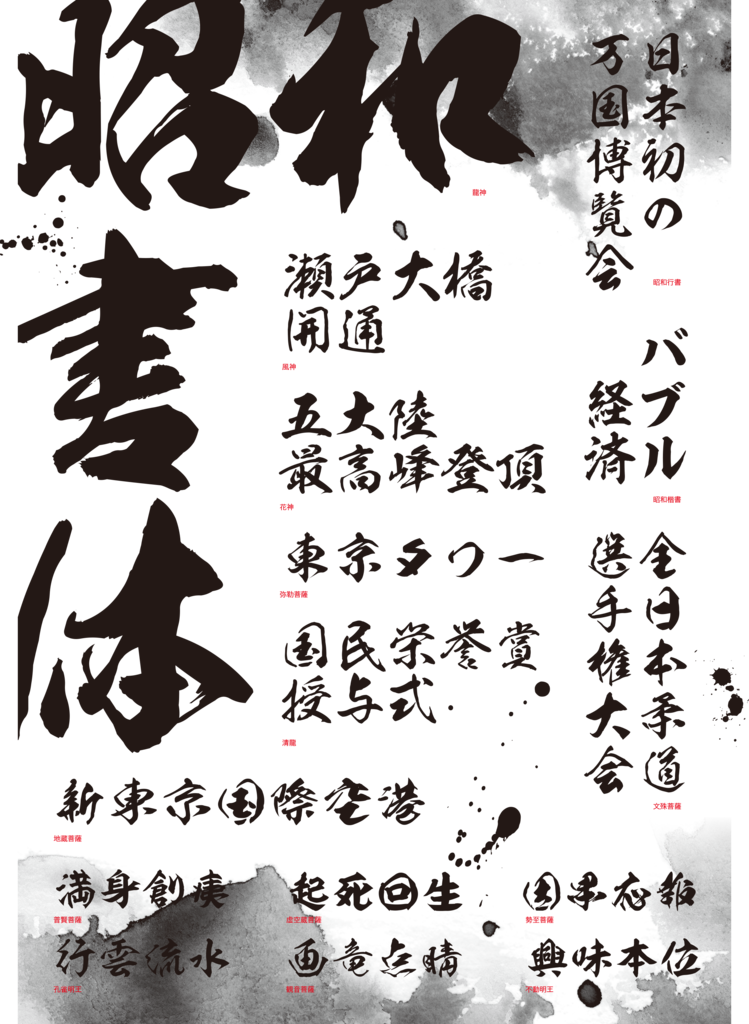
FONT x FAN HYBRID 5(フォントファン ハイブリッド 5)特長
1.コスパ度国内最大の総合フォントパック集
個別のフォント製品や日本語総合フォント製品を多数収録。
2.国内最多規模のフォントパック
国内最大級となる12817のフォントを収録、年間ライセンス製品ものはもちろん売り切り型のフォント製品の中でも最大規模の収録となる。
3.FONT x FAN HYBRIDシリーズ第5弾!今回も増量&大幅パワーアップ
新作、未公開フォントなど日本語フォント34フォント、欧文フォント228フォントなど多数追加収録
5.初回特典として迫力ある筆文字として人気の昭和書体『昭和書体セレクトパック2(ダウンロード版、定価7,000円)』を特別収録。
多用し易いベーシックフォントから人気の筆文字系、デザイン系まで広く収録。プロ用をはじめ人気のUD書体、デザイン筆文字その他新作フォントを追加収録。
クリエイターズ手書き風仮名フォント『ガールズフォント』/ OpenType
レトロ風,シネマ風等収録した『レトロ仮名フォント』/ OpenType
タイトルに最適なカナフォント集『カナフェイス44』/ TrueType
ちらしやPOPに最適なクリエイターズ数字フォント『NUMBER FONT』
デザイン欧文フォント集『DESIGN FONT PACK VOL1』、『DESIGN FONT PACK VOL2』
世界の欧文フォント集『KeyFonts DX Hybrid』
国内外のフォントクリエイター71組参加による厳選1986書体
『クリエイターズフォントバイブル』 / TrueTypeまたはOpenType
昭和書体の筆文字欧文フォント集 『昭和書体欧文フォント114』 / TrueTypeまたはOpenType